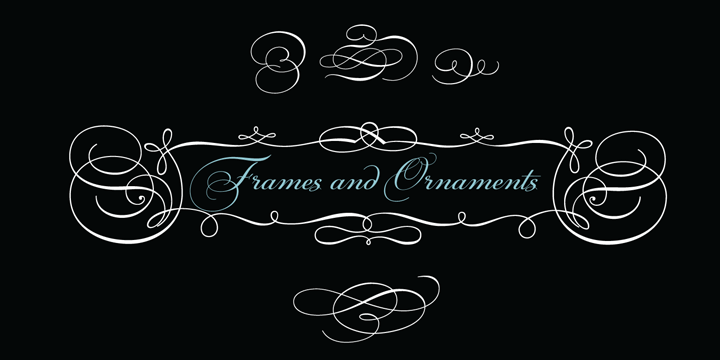
Textabschnitt Zeichen gesucht
dieses Zeichen ist aus dem Zeichensatz von Adobe® Wood Type® Std Regular
Leider ist die Auswahl nicht sonderlich groß und ich suche weitere dieser Zeichen.
Weiß jemand von euch welche (vorzugsweise System-)Schriften über ein besonders großen Zeichensatz
mit solchen Ornamenten verfügen? Vielen Dank!
Hier hat sich vom Bleisatz zum Computerfont eigentlich nichts geändert. Schmuck-Elemente, Vignetten und Linien waren nie Bestandteil einer Schriftart, sondern gesondert gelieferte Sätze, genau so muss man hierfür so genannte Dingbat-Fonts einsetzen. Auch bei Freefonts gibt es da eine ganze Menge brauchbares Zeug:
Besonders gut gefallen mir hier die Vignetten von Intellecta Design , auch hier zu bekommen:
Also den einen oder anderen Font, der Schrift mit dazu passenden Ornamenten vereint, scheint es schon zu geben.